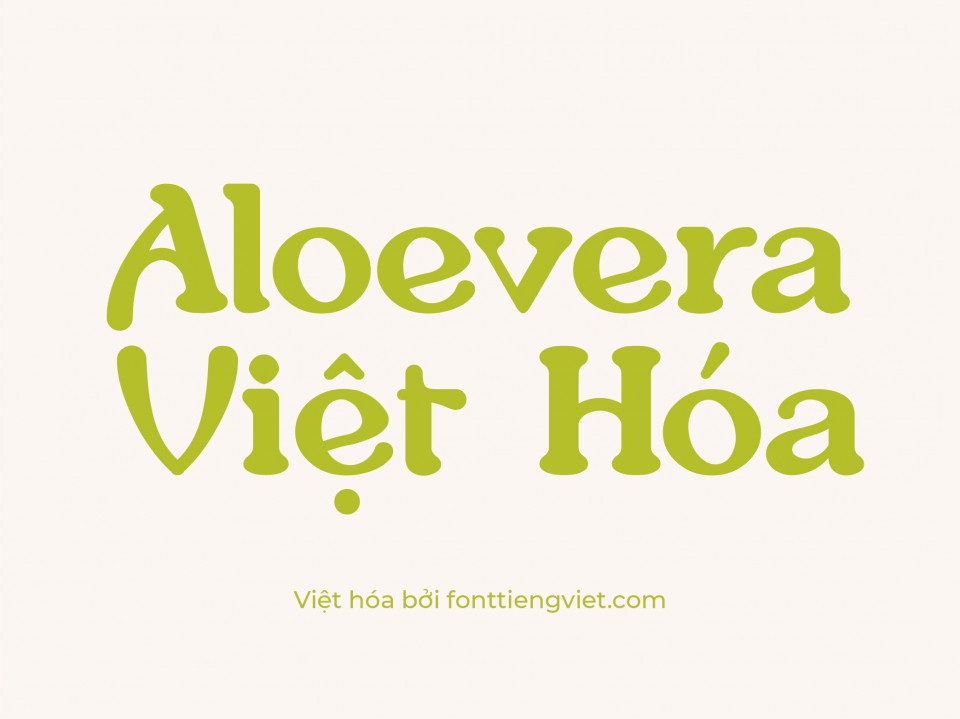
Font việt hóa 1FTV Aloevera
Giới thiệu về bộ Font việt hóa 1FTV Aloevera
Trong thế giới đồ họa hiện đại, việc tìm kiếm một bộ Font Miễn Phí chất lượng cao luôn là ưu tiên hàng đầu của các nhà sáng tạo. Font việt hóa 1FTV Aloevera nổi lên như một lựa chọn hoàn hảo nhờ sự kết hợp tinh tế giữa nét chữ hiện đại và phong cách viết tay mềm mại. Đây là bộ phông chữ được tinh chỉnh kỹ lưỡng để phù hợp với bảng mã tiếng Việt, giúp người dùng không còn lo lắng về lỗi hiển thị dấu khi thiết kế các ấn phẩm truyền thông hay bài giảng học đường.
Ưu điểm nổi bật của Font việt hóa 1FTV Aloevera
Thiết kế thanh lịch và đa dụng
Đặc điểm ấn tượng nhất của Font việt hóa 1FTV Aloevera chính là những đường nét uốn lượn tự nhiên, tạo cảm giác gần gũi nhưng không kém phần sang trọng. Bộ chữ này cực kỳ phù hợp cho các thiết kế thiệp mời, bìa sách, hoặc các dự án nghệ thuật đòi hỏi tính thẩm mỹ cao. Với độ dày nét vừa phải, phông chữ đảm bảo tính dễ đọc ngay cả trên màn hình điện thoại và các bản in khổ lớn.
Tương thích tốt với nhiều phần mềm